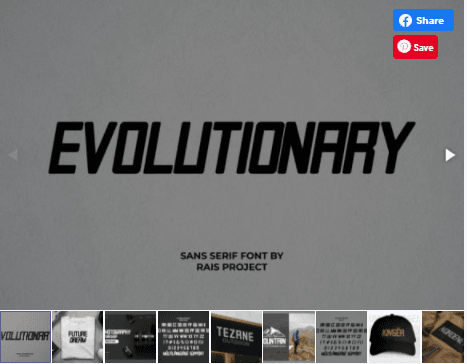
Evolutionary Font
Evolutionary - это классный робот без засечек. Он будет потрясающе смотреться на любом плакате, флаере или принте.
Используйте этот шрифт для своих проектов и исследуйте его безграничные возможности.